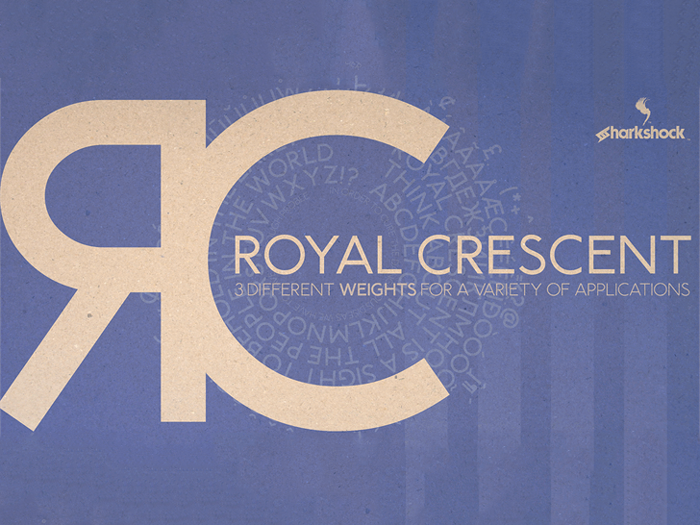
Royal Crescent Font – Download Grátis
A Royal Crescent é uma elegante sans serif que se destaca por sua simplicidade e modernidade. Desenvolvida pelo Designer Sharkshock, esta fonte traz três opções de estilos: regular, bold e light, criando um equilíbrio perfeito entre força e suavidade. Oferecida em formato OTF, a Royal Crescent é uma escolha ótima para quem busca uma tipografia moderna que se adapta facilmente a diversas aplicações gráficas, desde materiais de design editorial até elementos digitais e aplicativos web. Sua simplicidade não compromete a qualidade: cada caractere mantém o equilíbrio perfeito entre linhas finas e espessuras, proporcionando uma legibilidade excepcional em todas as resoluções. Com todos os direitos reservados pela Sharkshock, esta fonte é um investimento valioso para designers e profissionais do design gráfico que desejam incorporar uma ferramenta poderosa a seu arsenal.